Yeah let's take the red pill
Wie vindt het soms lastig om lettertypes te combineren 🙋♂️? Eigenlijk check ik vaak alleen of de x-hoogtes gelijk zijn en is het voor de rest vooral onderbuikgevoel. Veel mensen vinden font pairing lastig, want waar moet je op letten?
Oliver Schöndorfer is een Oostenrijkse UI-designer/typograaf en heeft een methode ontwikkeld die het makkelijker maakt om lettertypes te kiezen die bij elkaar passen. Hij noemt het de Font Matrix en de theorie is gebaseerd op het werk van Indra Kupferschmid. Ik vond het erg verhelderend allemaal.
Oliver legt z'n methode uit in deze video, en ik doe mijn samenvatting daaronder:
Lettertypes worden vaak gecombineerd op basis van categorieën. Bijvoorbeeld schreef combineren met schreefloos - maar die twee categorieën zijn enorm breed en erbinnen zijn veel verschillen. Of je combineert op basis van historische classificaties - maar dat is vaak onpraktisch en verwarrend (Bodoni uit 1786 wordt Modern genoemd en Times New Roman uit 1931 wordt Transitional Old Style genoemd 🤔).
Daarom heeft Indra Kupferschmid een nieuwe manier bedacht om lettertypes te categoriseren. Niet gebaseerd op type history maar op visuele kenmerken. Hierdoor zul je zien dat Helvetica en Bodoni een echt liefdeskoppel zijn terwijl ze honderden jaren in leeftijd verschillen ❤️
Hoe het werkt? Kies op basis van visuele kenmerken een van de opties binnen de volgende drie onderwerpen:
Vorm
De vorm is dynamisch: de letter heeft open vormen en de letterhoek (the stress) is diagonaal
De vorm is rationeel: de letter heeft gesloten vormen en de letterhoek (the stress) is verticaal
De vorm is geometrisch: de letter heeft geometrische vormen
Schreven
De letter heeft schreven
De letter is schreefloos
Contrast
De letter heeft veel contrast, dus veel verschil tussen dikke en dunne delen
De letter heeft weinig contrast, dus weinig verschil tussen dikke en dunne delen
Samen maakt dat de Font Matrix:
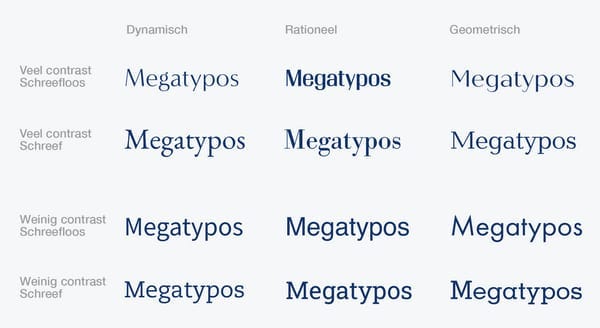
Nu we een praktischere manier hebben om lettertypes te categoriseren, kunnen we ze makkelijker pairen. Vuistregels bij bovenstaand overzicht: lettertypes in dezelfde verticale kolom combineren mooi met elkaar; lettertypes in dezelfde horizontale rij combineren slecht met elkaar. Et voilà!
En daarom houden Helvetica en Bodoni dus van elkaar!
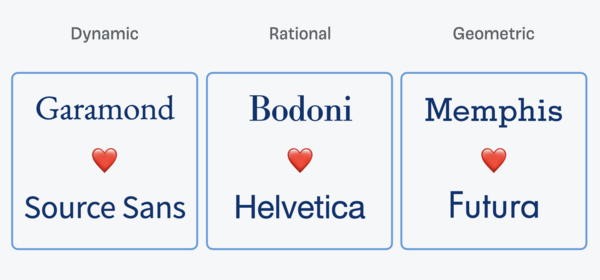
Lees de uitgebreide versie in Oliver's blogpost. Of doe mee aan de online course over dit onderwerp die hij gisteren is gestart.
Figma heeft de video's van alle sprekers op Config 2022 online gezet. Het zijn er meer dan 70; ik heb deze drie bekeken:
Join José for a story about design systems and gardening. First, he will break some misconceptions about the design systems role in the world of product design, using his perspective as a craft leader working on one of the most well respected systems in the industry: Shopify Polaris.
As Klarna skyrocketed with expansion in non-Latin markets, the team had to rethink from scratch typography in their products moving to system font stack and swap it in their design system—in this talk, Francesco will talk about how they did that.
In this talk, Fons will talk about his creative process and the role Figma plays in it.
MUST: JOCHEM LEEGSTRA
Jochem is Halfvetter, snelle denker, snelle prater, maar geen snelle jongen. Daarnaast founder & creative director van …,staat.
Inspirerend design festival:
Meerdere, maar twee die er voor mij uitspringen: inhoudelijk sterk én verrassend is zeker ons Nederlandse What Design Can Do. Deze conferentie zit zo goed op het nut van design en creativiteit. In letterlijk alle werelden. Raakte me emotioneel ook echt. En gaat veel verder dan de vaak gekozen design-kant van design.
Iets totaal anders qua vibe, opzet, energie, lokatie, aantal sprekers en de algehele creatieve context (én goed eten) is USBYNIGHT in Antwerpen. Onder leiding van gastheer en 3D-artist Rizon Parein. Meer een echt festival. Zoals de naam al zegt is het festival niet overdag. Helpt ook. Besef me opeens hoeveel we de festivals en conferenties hebben moeten missen de afgelopen 2 jaar…